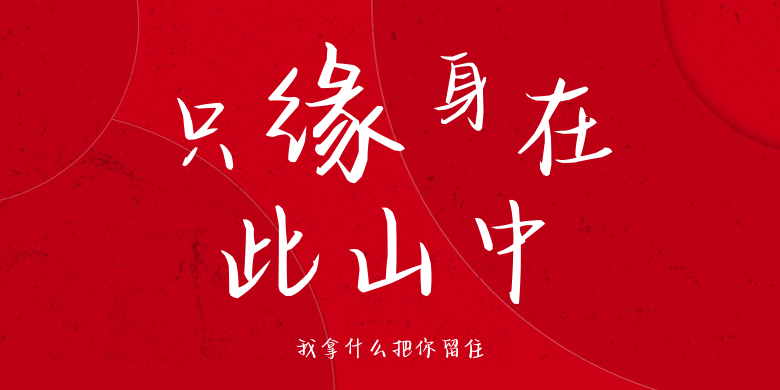
我拿什么把你留住
我拿什么把你留住,这款字体结构工整、笔画清晰,兼顾美观与易读性,适用于标题、正文、海报、包装、LOGO 等多种场景。字形优雅稳定,风格百搭耐看,适配日常排版与创意设计,让文字呈现更舒适、更具质感。我拿什么把你留住一笔一画,皆是细节,以均衡的比例、流畅的线条打造舒适视觉体验,字形端正大气,风格简约现代。无论是商业设计、品牌宣传还是日常排版,都能轻松驾驭,让文字更有格调与力量。我拿什么把你留住字体下载。